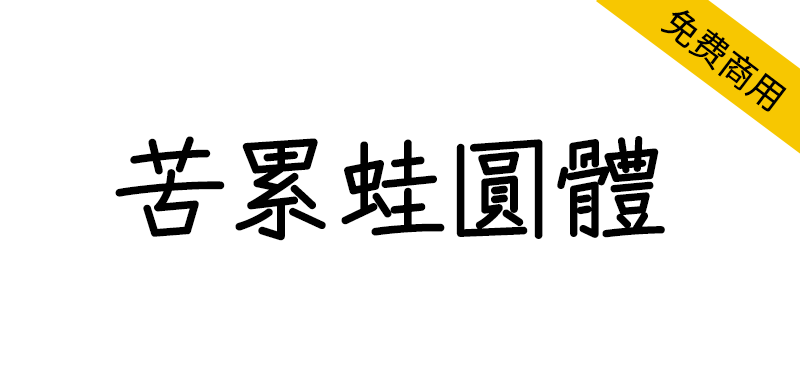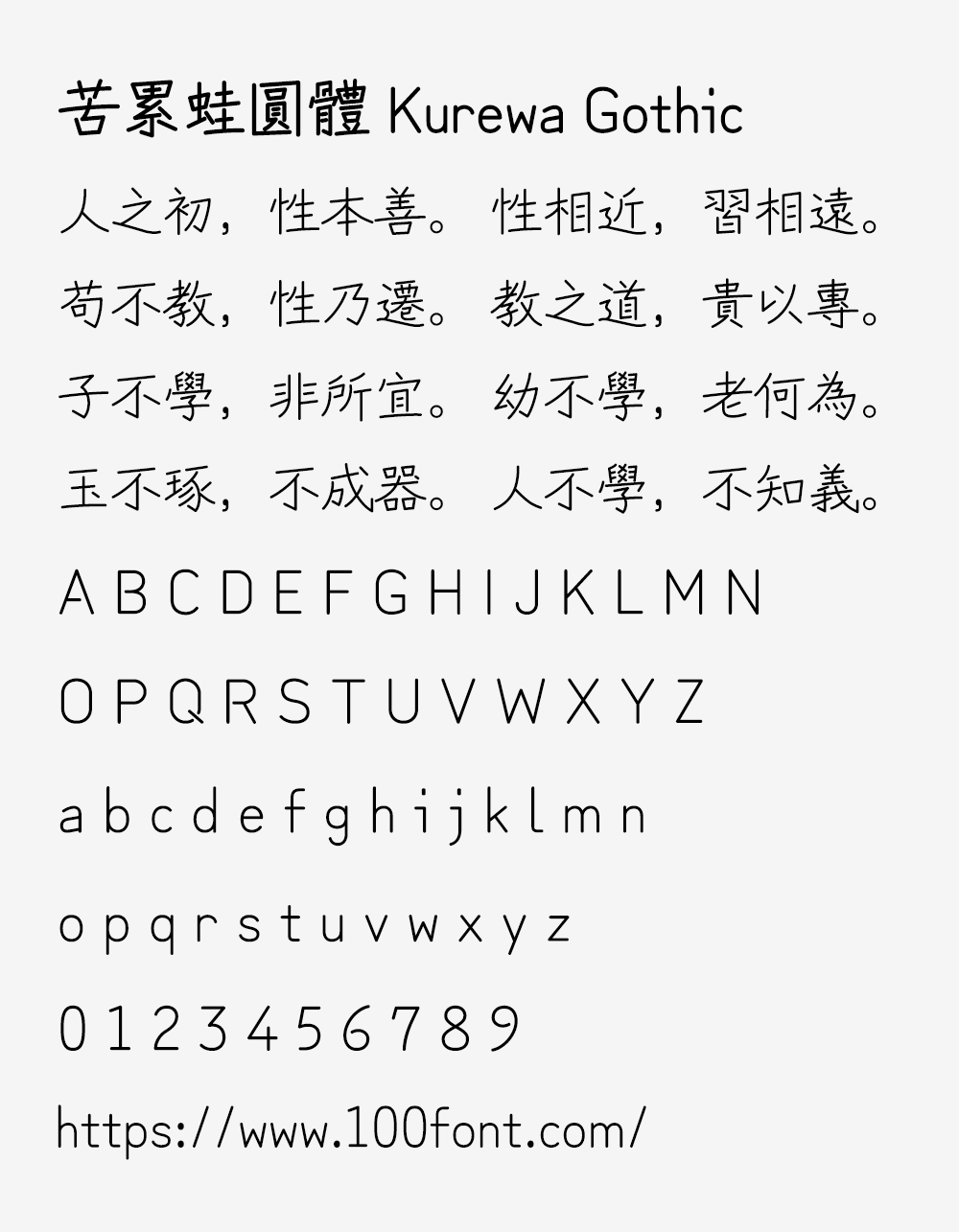
苦累蛙圆体(Kurewa Gothic)是Zen红道手写体的补字计划,与原作者的主要差异是调整部件写法、新增中文字、增加为5个字重、增加一些符号。可以免费商用,欢迎大家自由应用、自由优化、自由改作!
字体特色:弥补繁体中文常用字缺字缺憾,调整为5种字重,标点符号位置调整为台湾常见的置中用法,增加台湾闽南语和客语的部份中文字,调整部件写法(相同一個字,在不地區的書寫方式可能會略有不同,原作者的字都放 CJK JP的檔案裡)。